그동안 만든 폰트는 손글씨였기 때문에 스캔해서 벡터화하면 데이터가 삐뚤빼뚤한 느낌이 있었는데 주말에 샘플로 다시 Stroke 기반으로 제작해 봤습니다.
초성 3벌 중성 2벌 종성 1벌을 기준으로 폰트를 만들었고 약 3시간 정도 제로에서 시작해서 일러스트레이터로 제작했습니다.
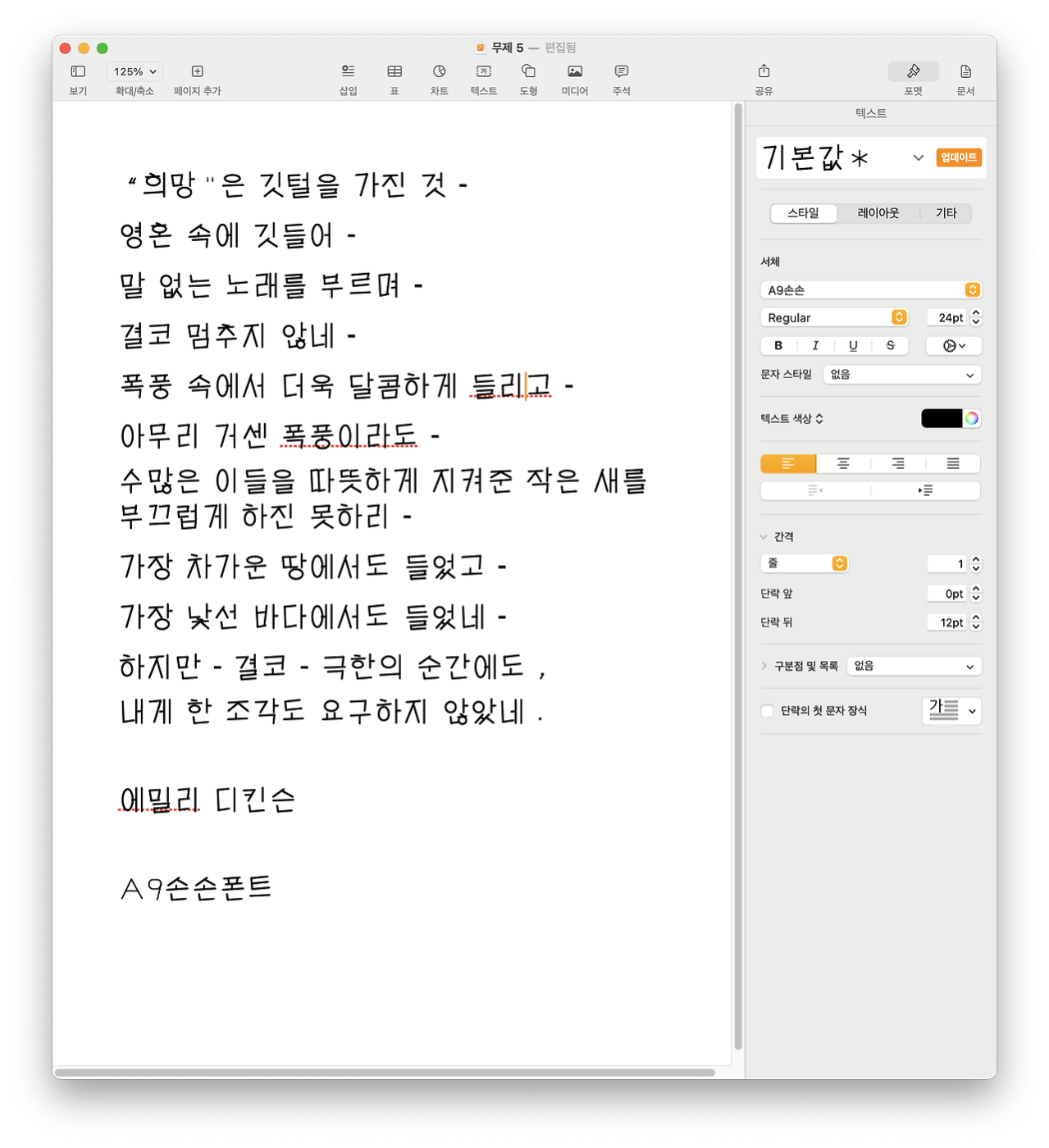
일일단 폰트는 일러스트레이터에서 한 화면을 보고 작업하기 때문에 어느 정도 균형미를 유지할 수 있습니다. 물론 수정해야 하고 글자 하나하나 개성을 줄 수도 있어 기존에 작업한 조합형 방식과는 달라집니다.
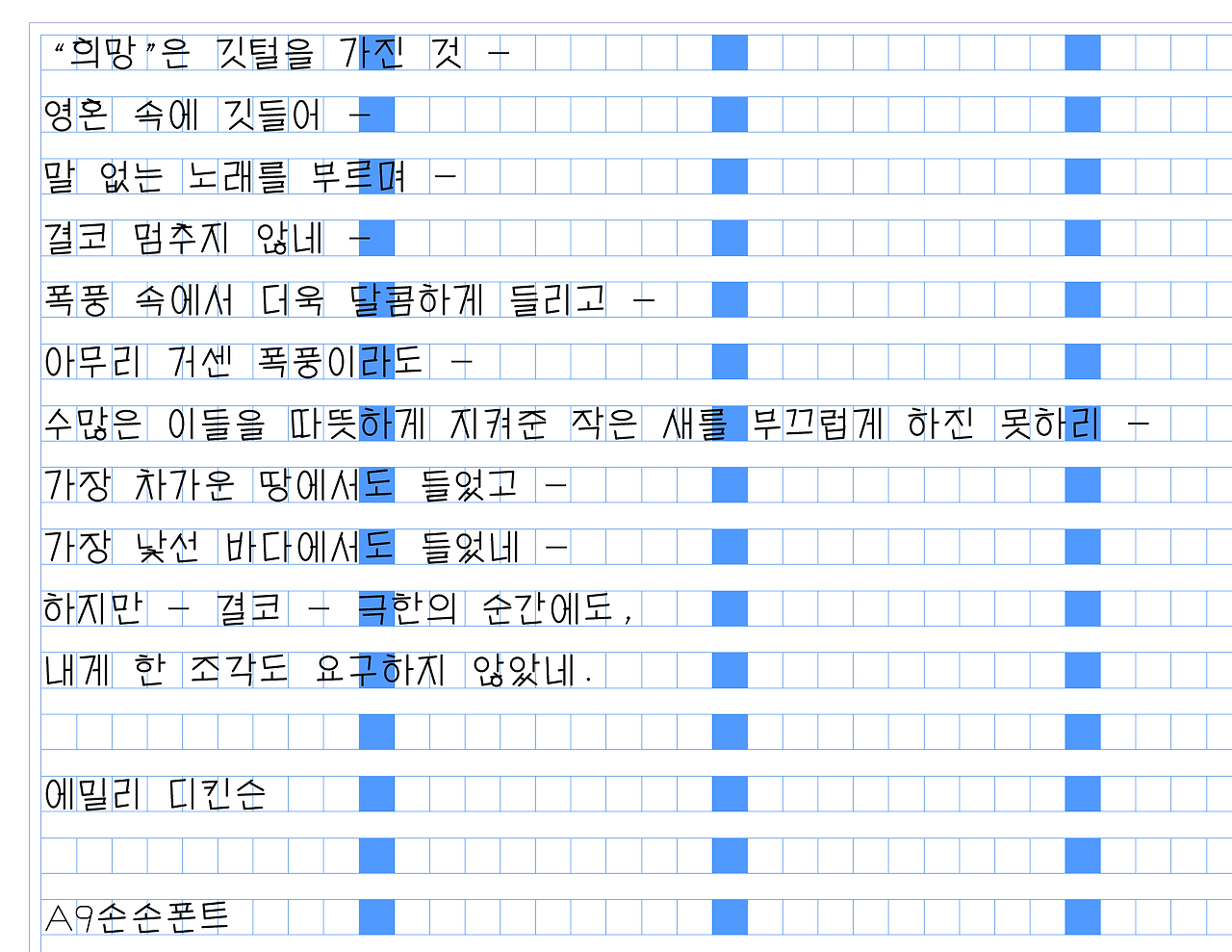
일단 가로 세로를 한 번에 작업하기 때문에 일정하게 균형을 유지할 수 있습니다. 특히 세로줄의 ㅏㅣㅖㅒㅞㅟㅘㅙ 등의 모양을 기준으로 잡고 작업을 하며 ㅗㅡㅜㅠㅛ 와 같은 가로줄의 가이드를 맞출 수 있습니다. 작업에 대한 방법론은 영상으로 남기겠지만 일단 방법론에 대해서 이야기드립니다.
초성과 함께 표시됐을 때 ㅗ 의 I자의 크기가 높낮이가 다를 수 있습니다. 그걸 한 화면에서 다 다르게 편집하면 그대로 폰트로 생성됩니다. 지금까지는 ㅗ의 높이가 조합된 한글 자모의 모양에 따라 바꿀 수 없었기 때문에 디자인 하나 고치면 다른 곳에서 달라지고 그걸 수정하면서 글꼴 자체가 원 글자체와 달라지는 미묘한 현상이 생겼습니다.
현재 방법으로는 개별 글자 하나도 편집이 가능하기 때문에 착시나 초성에 따른 중성의 조합을 신경 써서 작업하면 그러한 일은 생기지 않습니다. 초성 ㄱ ㄲ, ㄷ ㄸ, ㅅ ㅆ, ㅈ ㅉ 쌍자음의 위치에 따라 ㅓㅖ같은 중성에 따라 글자의 너비가 달라집니다. 공간을 잘 배열하고 채우기 위해 가이드를 깔아 놓고 하나하나 작업하던 기존의 폰트 제작방식도 심벌에 가이드를 깔고 작업하면 됩니다.
세로를 기준으로 제작하기 때문에 작성하고 바로 만든 폰트도 세로 쓰기로 봤을 때 잘 나와 보입니다. 빨리빨리 작업하기 위해 Stroke로 만들었지만 제대로 작업하면 기존 글꼴을 대체하는데 무리 없어 보입니다.
더 많은 테스트가 필요하고 그럴듯한 폰트 샘플 (문서용 폰트)을 제작해야 하지만 현재 그것보다는 일러스트레이터 플러그인이나 컨버팅 서비스를 만드는 게 더 급하다 생각되어 우선순위를 정해 진행하려고 합니다.
일단 제대로 하나의 폰트를 완성해 보기로 외국폰트의 서체특성을 기준으로 한글버전 라이선스를 해볼까 하고 있습니다.